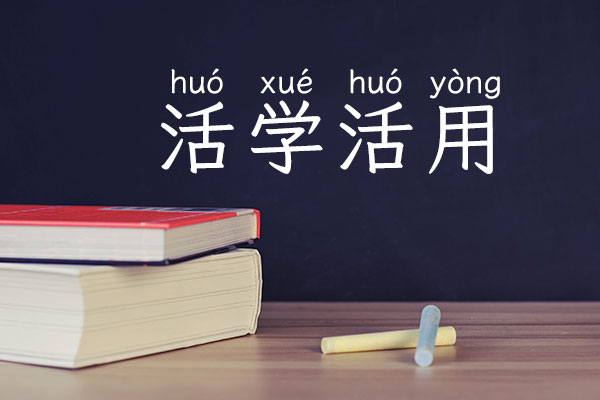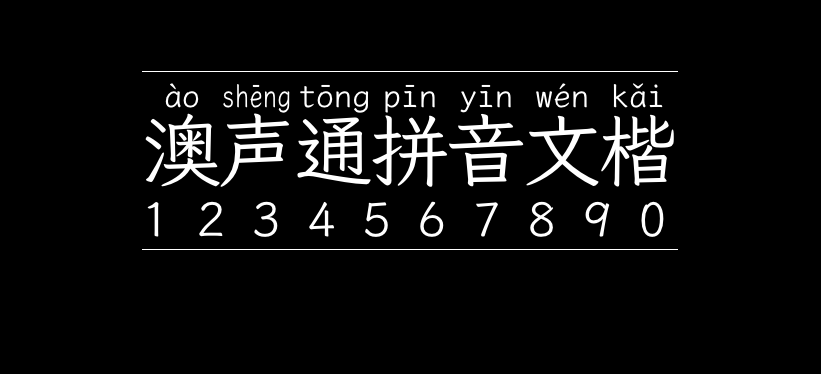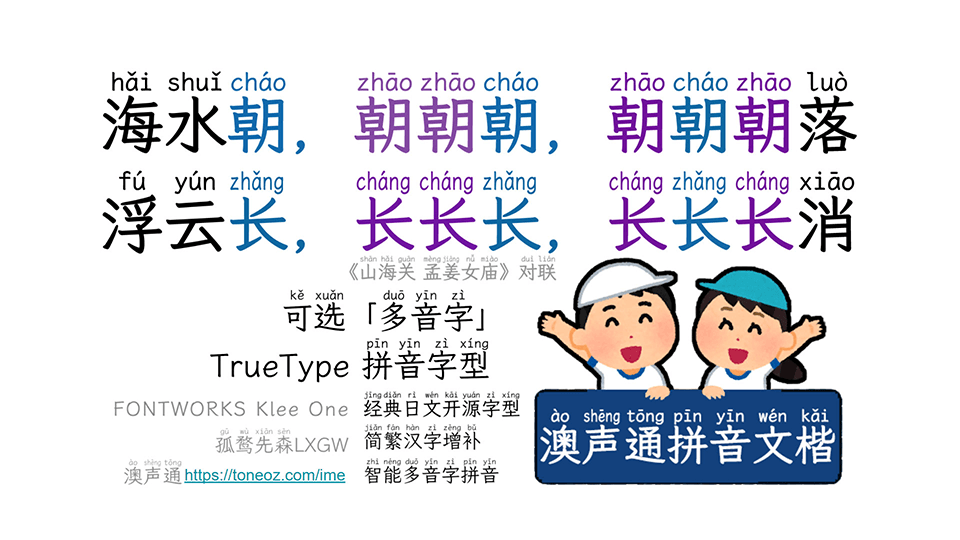
澳声通拼音文楷
澳声通拼音文楷是一款基于克利Klee One以及霞鹜文楷的制作中文字体,可以搭配免费免安装在线多音字选音工具澳声通使用。
澳声通拼音文楷由于是基于两款成熟的开源字体进行二次制作,所以无论简体还是繁体基本上不存在缺字,而且还支持了数量繁多的多音字。更值得一提的是,澳声通拼音文楷支持3个字重。